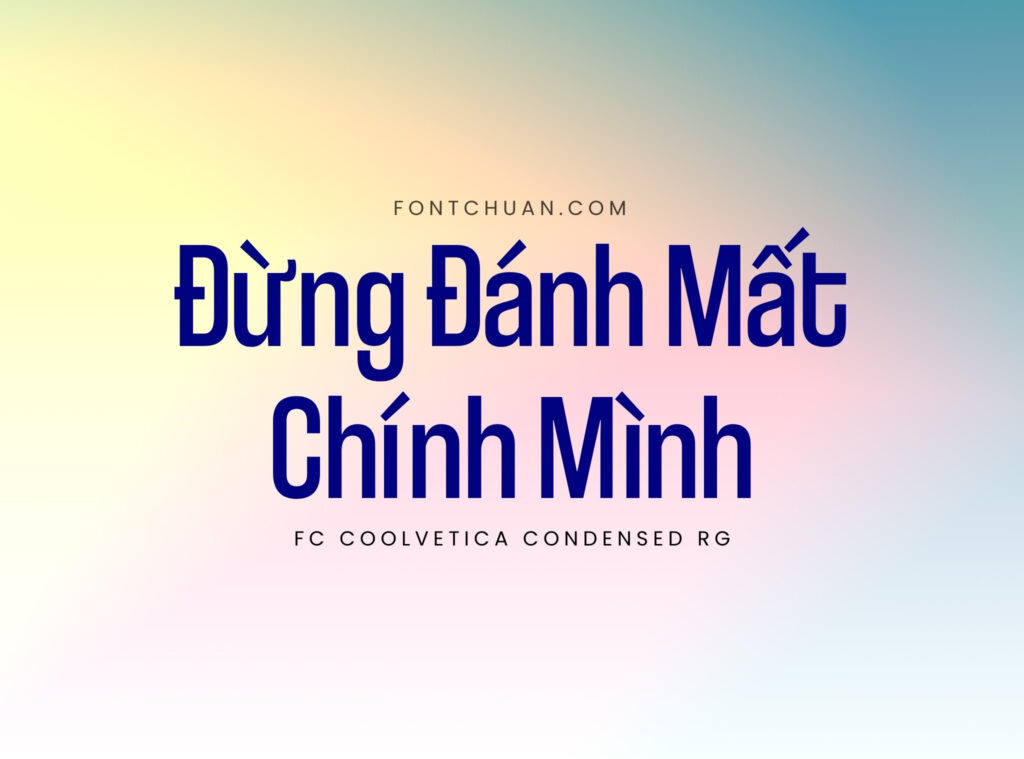
Coolvetica Condensed Rg là một biến thể của họ font Coolvetica, được thiết kế bởi Ray Larabie và phát hành bởi Typodermic Fonts. Lấy cảm hứng từ các thiết kế logo Mỹ những năm 1970, Coolvetica mang phong cách sans-serif với các đường nét đơn giản, sạch sẽ và thanh lịch. Phiên bản Condensed Rg có thiết kế hẹp hơn, phù hợp cho các tiêu đề, logo và các dự án thiết kế cần sự tinh tế và hiện đại, thậm chí có thể ứng dụng linh hoạt như một font chữ Trung Thu trong các ấn phẩm lễ hội theo phong cách trẻ trung.
Font này mặc định đã hỗ trợ các ký có dấu tiếng Việt nhưng chưa hoàn chỉnh, nhóm Font Chuẩn đã chỉnh sửa và cập nhất để hỗ trợ tốt cho tiếng Việt, phiên bản mặc định hỗ trợ tốt cho tiếng Anh và nhiều ngôn ngữ Latin khác, bao gồm cả tiếng Hy Lạp và Cyrillic, mở rộng khả năng ứng dụng cho các dự án quốc tế.
Với cấu trúc chữ cân đối, độ dày vừa phải và thiết kế tinh tế, Coolvetica Condensed Rg phù hợp cho các thiết kế yêu cầu sự hiện đại và chuyên nghiệp. Đặc biệt, font này thích hợp cho các ngành nghề như quảng cáo, thiết kế thương hiệu và lĩnh vực truyền thông, nơi cần sự kết hợp giữa thẩm mỹ hiện đại và chức năng truyền tải thông điệp.